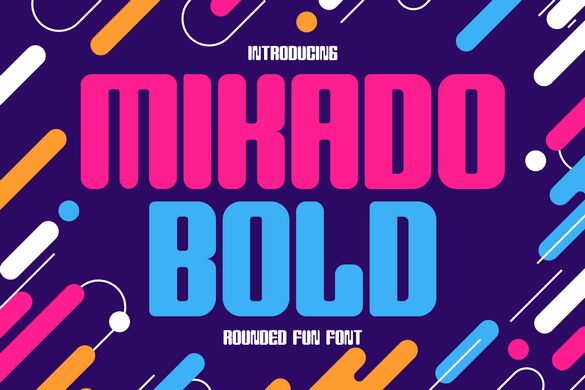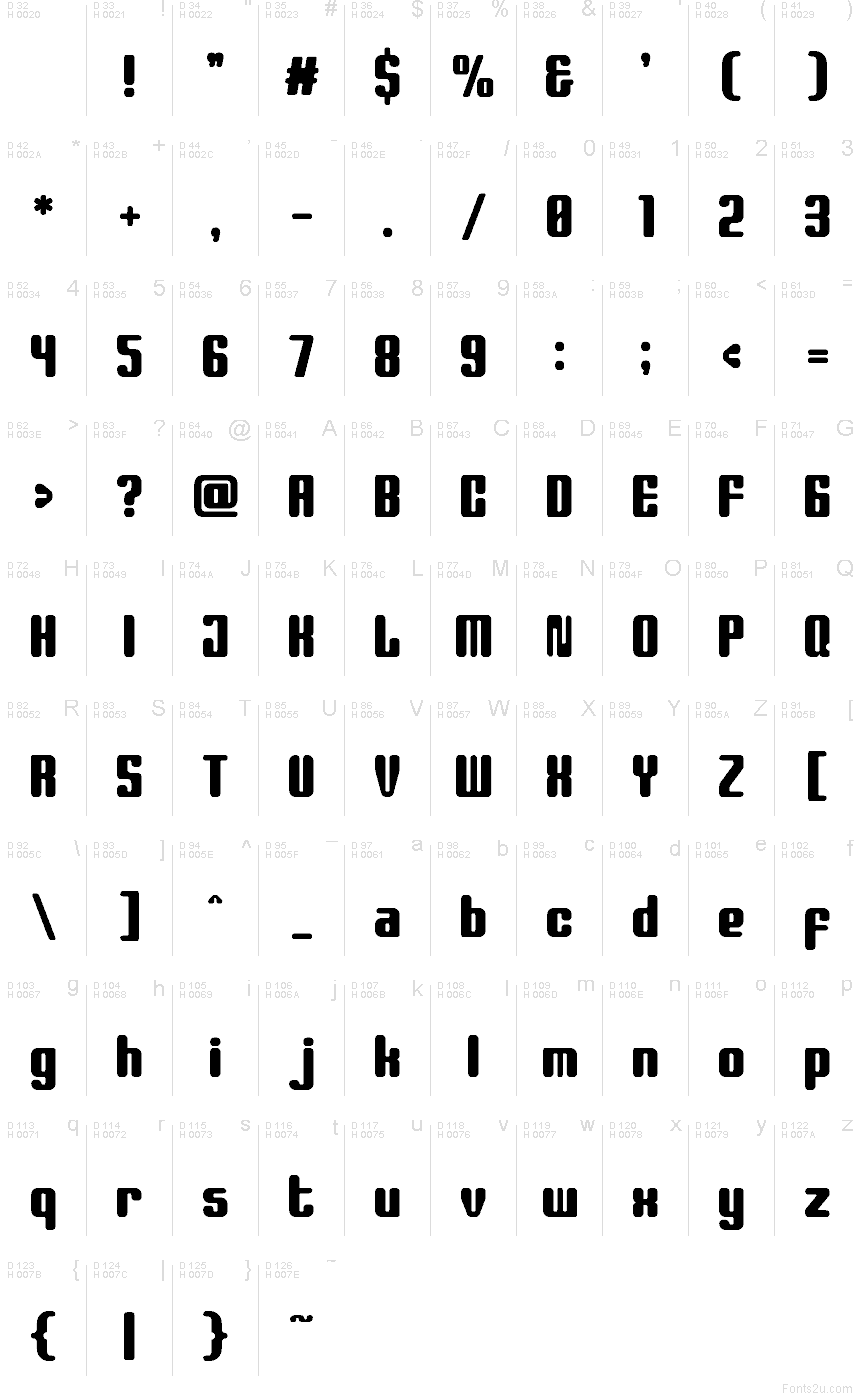
Mikado Bold von Shanaf Studio ist eine kostenlose, abgerundete, moderne Display-Schrift mit einem weichen, voluminösen Rhythmus. Die Buchstaben wirken aufgebläht und sympathisch, mit hohen, pillenförmigen Vertikalen, tiefen Kurven und engen Verbindungen, die dem gesamten Design eine geschmeidige, spielzeugartige Silhouette verleihen – fernab von scharfer Geometrie.
Sie eignet sich perfekt für das Branding von Jugendprodukten, Café-Menüs, Plakat-Überschriften, Verpackungen, App-Startbildschirmen und Titelkarten, bei denen eine kostenlose Schrift mit Wärme und Substanz überzeugen soll. Dank ihrer vollen, reduzierten Formen funktioniert sie auch hervorragend für Logos, Cover-Texte und großformatige Einzelwörter, die eine verspielte, zeitgemäße Note benötigen.